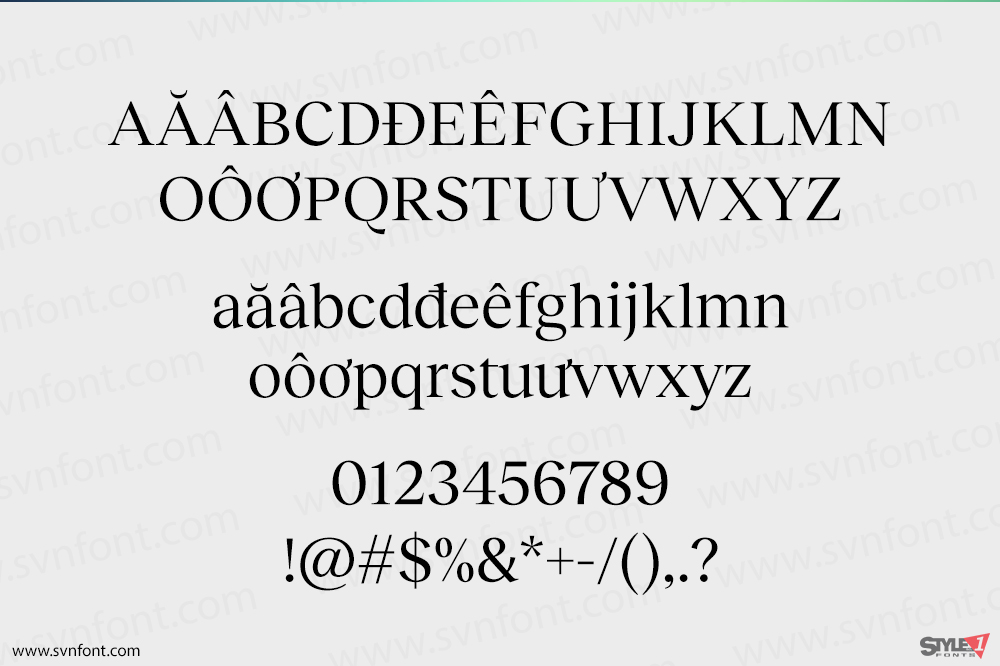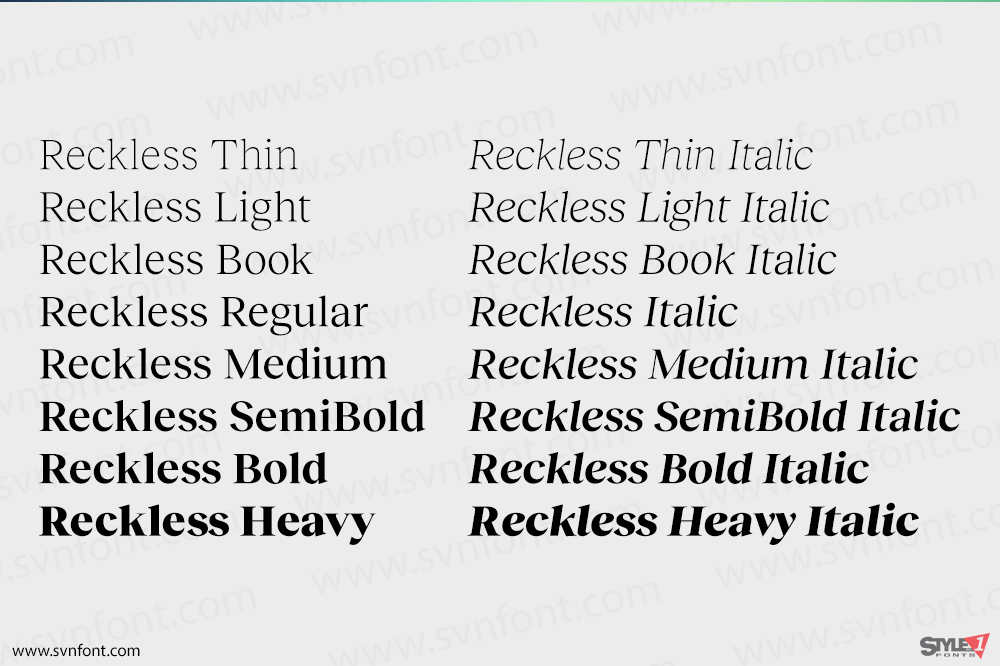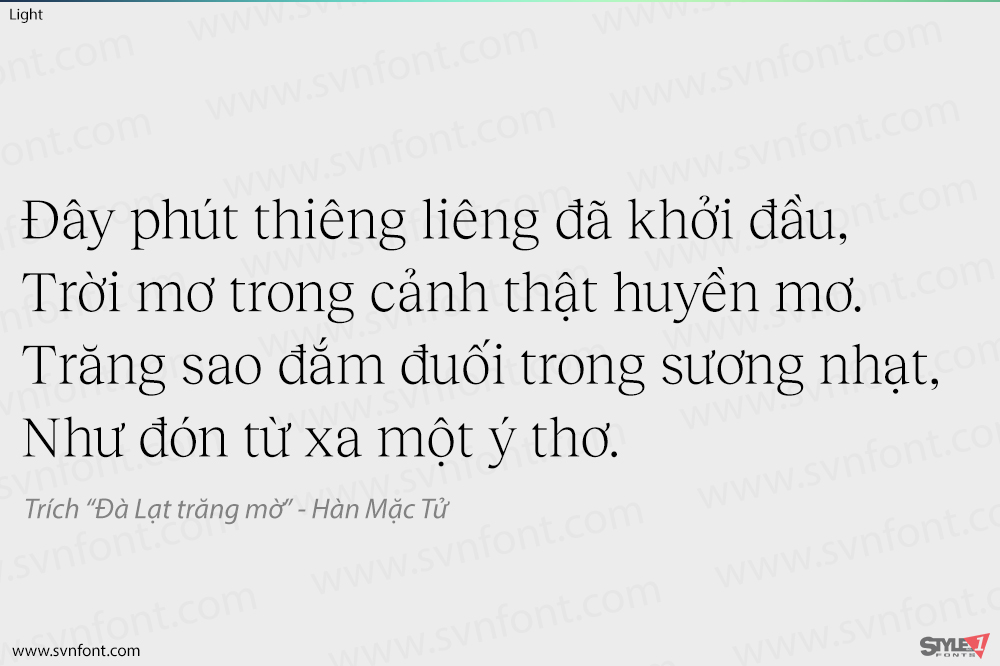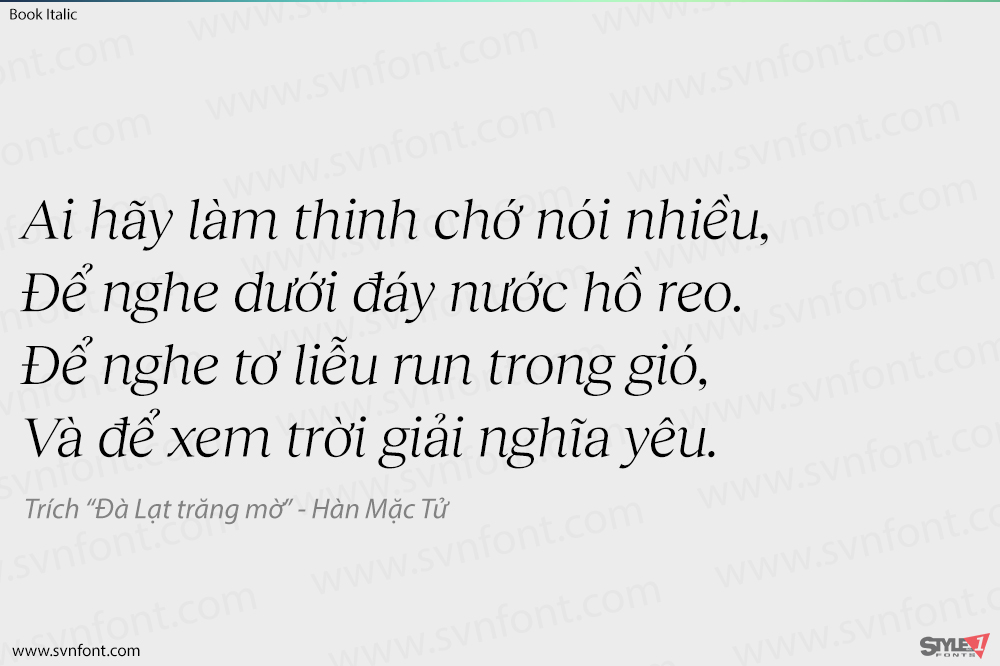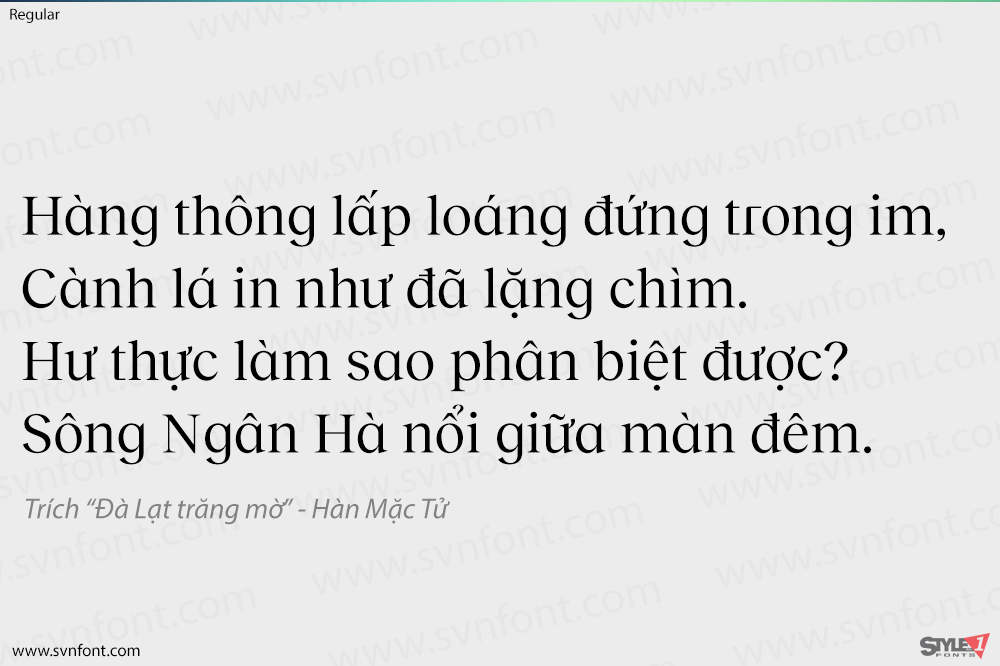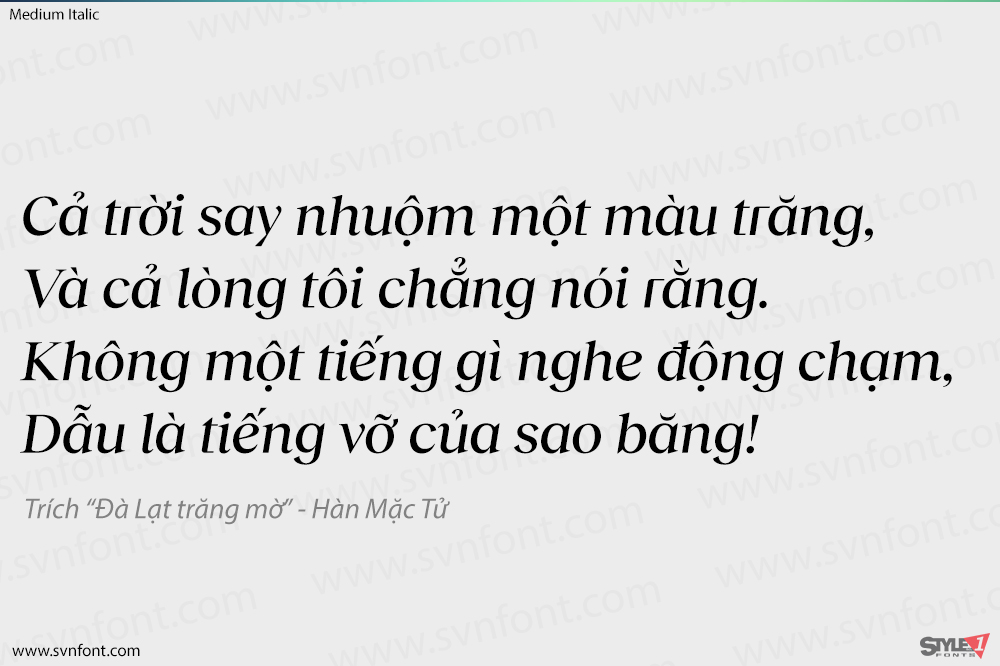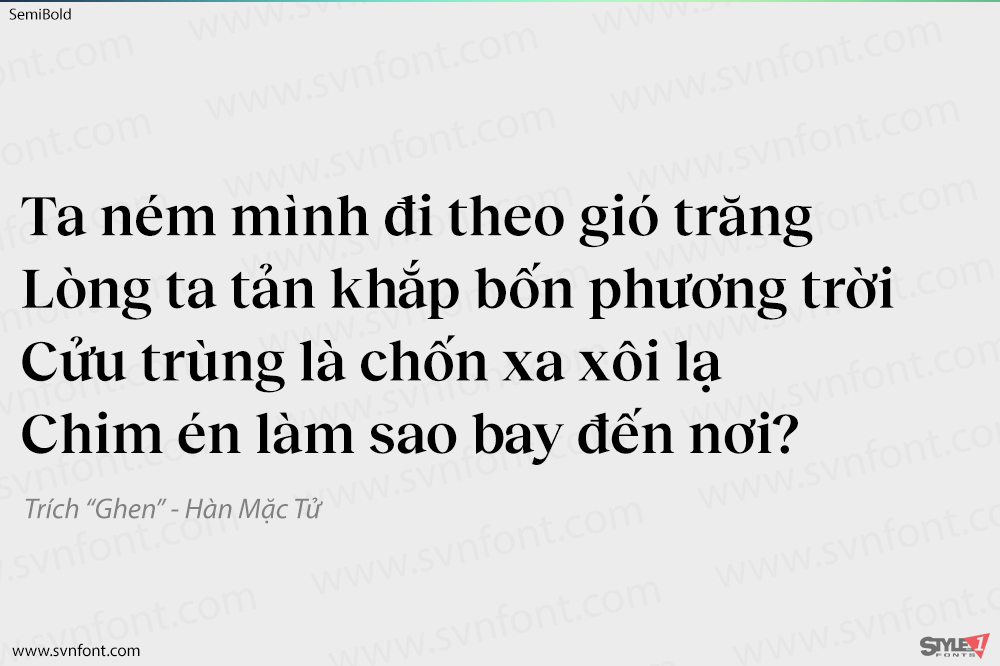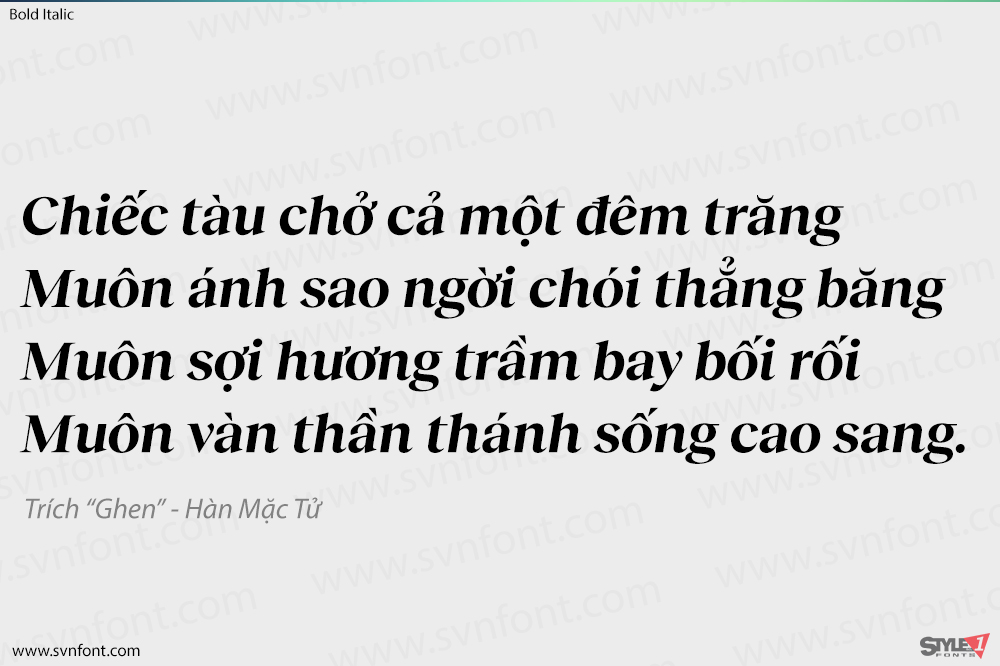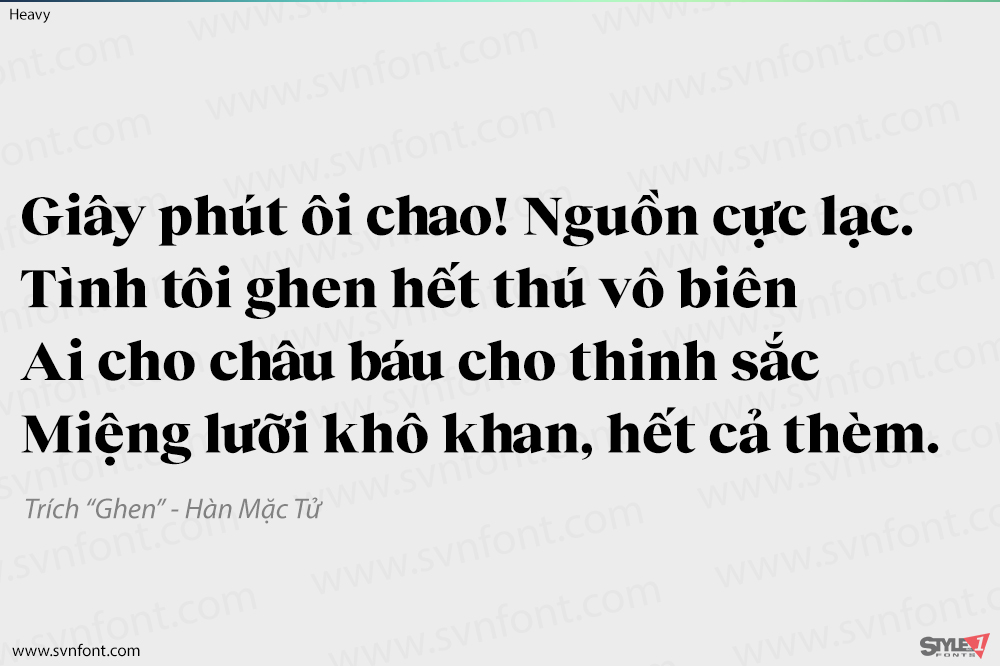
Reckless là một kiểu chữ serif mang đậm nét phục hưng (cổ điển) và có chiều cao x được nâng lên đáng kể. Nó được thiết kế trong quá trình nghiên cứu về sự phát triển lịch sử và các nguồn gốc của kiểu chữ serif tại nhiều thư viện khác nhau. Ý tưởng chính dựa trên các xu hướng thư pháp, được đưa trở lại từ các kiểu chữ serif ban đầu vào các cấu trúc đương đại. Reckless Neue là một phiên bản có độ tương phản cao hơn, bộ ký tự được sắp xếp lại và các độ đậm mới (Thin, Book).
Nhà thiết kế: Martin Vácha
Nhà phát hành: Displaay Type Froundry